“We zijn aan het einde van de cursus gekomen. Bedankt om het te volgen! Ik hoop dat dit leerproces nuttig voor je zal zijn en dat je met veel plezier je afstudeerproject zult uitvoeren. Dit is het moment om je eindproject voor te bereiden. Ik moedig je aan om je eigen creatie te maken en de tijd te nemen om inspiratie op te doen. Om je te helpen, laat ik je hieronder de belangrijkste stappen die je moet volgen om je afstudeerproject te voltooien. Je kunt afmaken waar je al aan begonnen bent met de oefeningen of je kunt een heel nieuw project starten! Zorg er in ieder geval voor dat u de verschillende stadia van uw creatie documenteert en een korte uitleg toevoegt over wat u in elk ervan hebt gedaan, evenals uw keuzes. Tekst en raster Kies een woord, zin of gedicht dat jou inspireert. Maak vervolgens een raster voor je typografische ontwerp, desgewenst eerst met de hand en later (of vanaf het begin) in Illustrator.
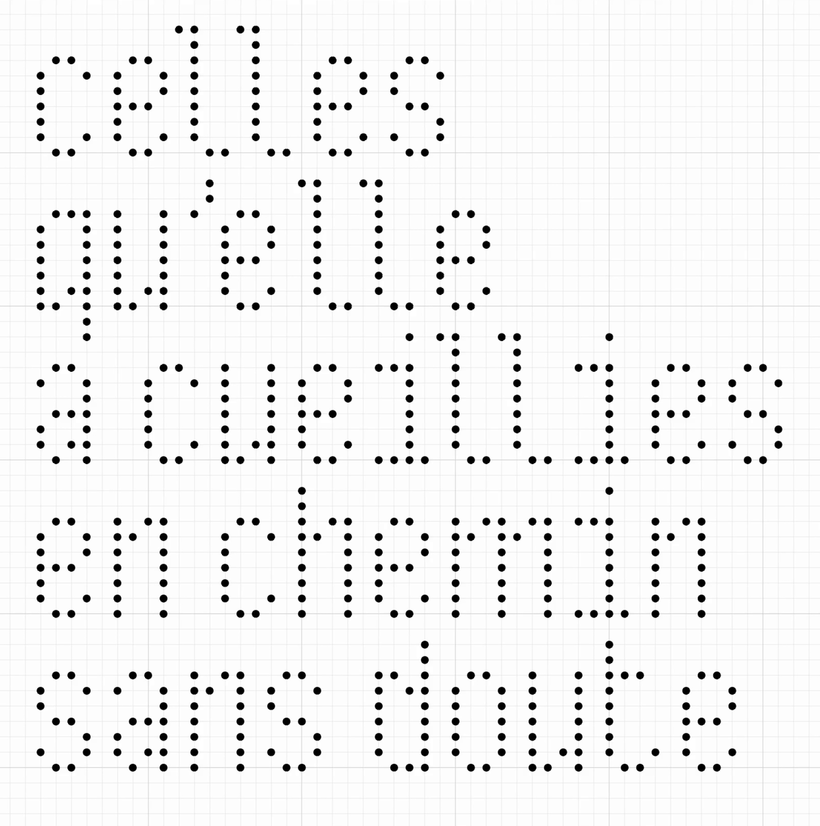
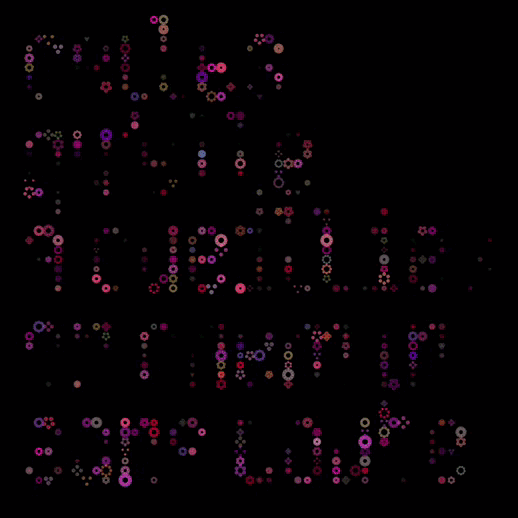
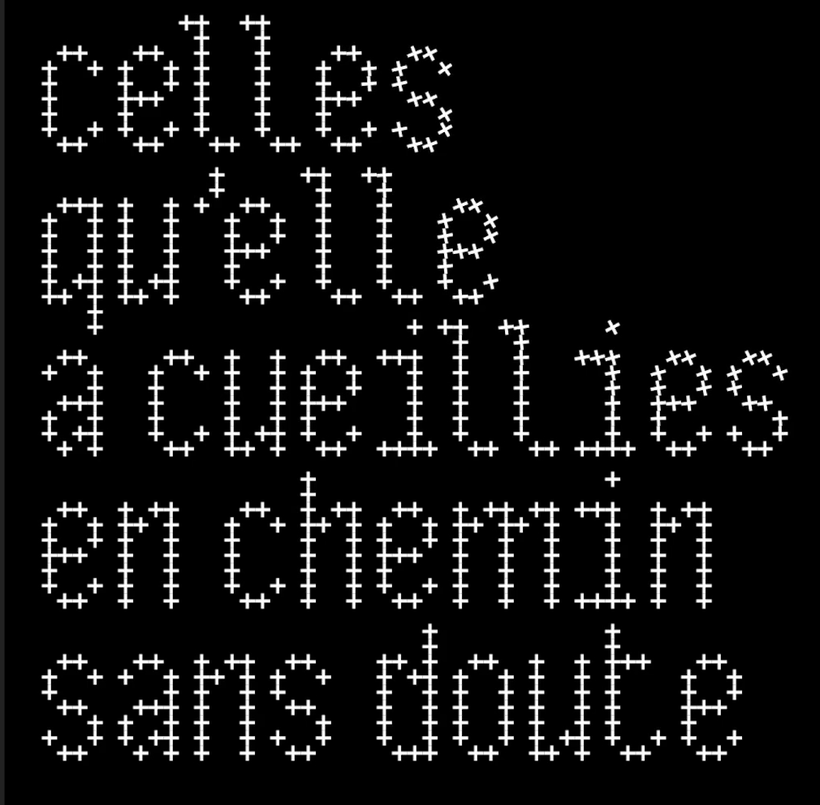
“Laatste project Bedankt voor het volgen van deze cursus. Ik hoop dat je het leuk vond en dat je duizend manieren zult vinden om het terug te winnen. Ik heb altijd van typografie gehouden voor de spellen maakt het mogelijk tussen het verstandige en het begrijpelijke, tussen wat wordt gezien en wat wordt gelezen. Het gebruik van typfouten op basis van geometrische vormen maakt de deconstructie van letters mogelijk en opent de mogelijkheid van nog meer spel. Voordat je begint, herinner ik je aan de hoofdfasen van de cursus om tot je eindproject te komen. Ik begon met het delen van mijn visie o...”